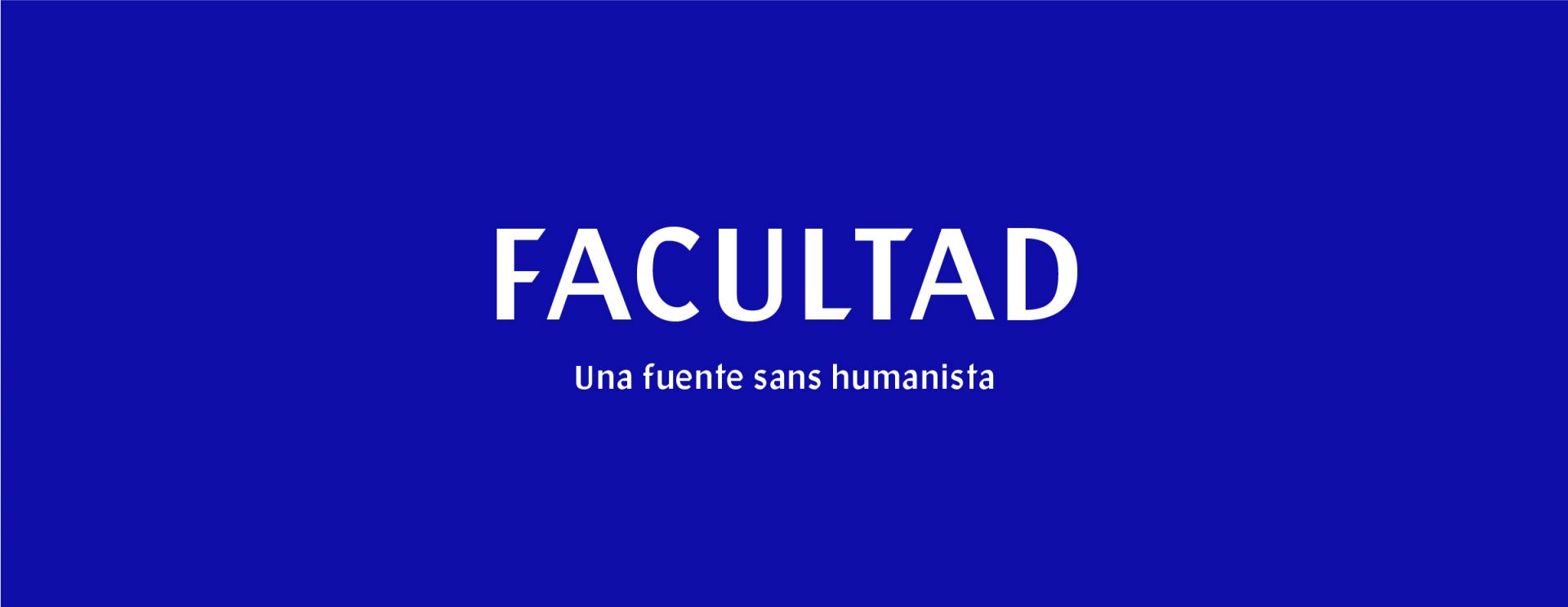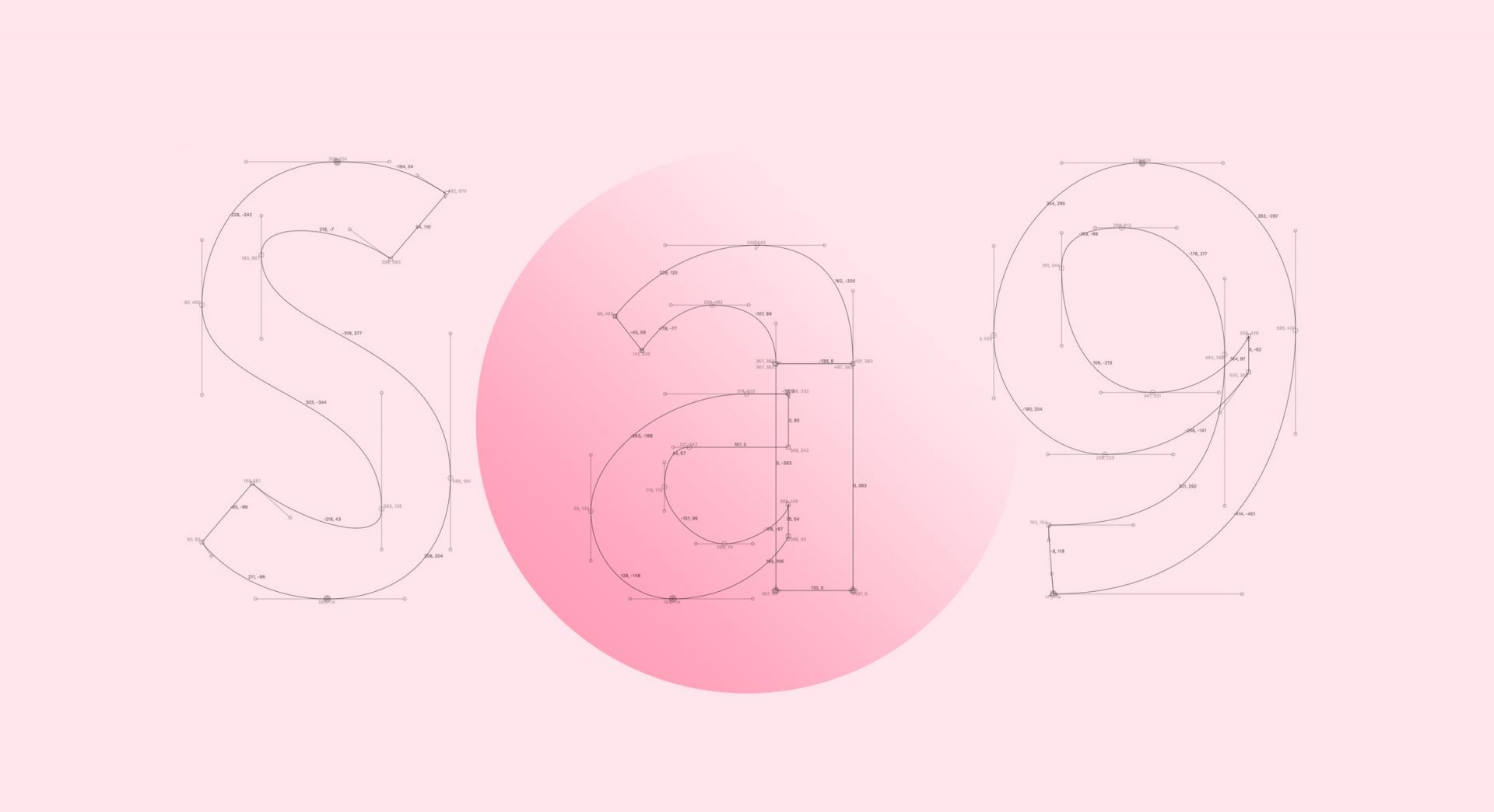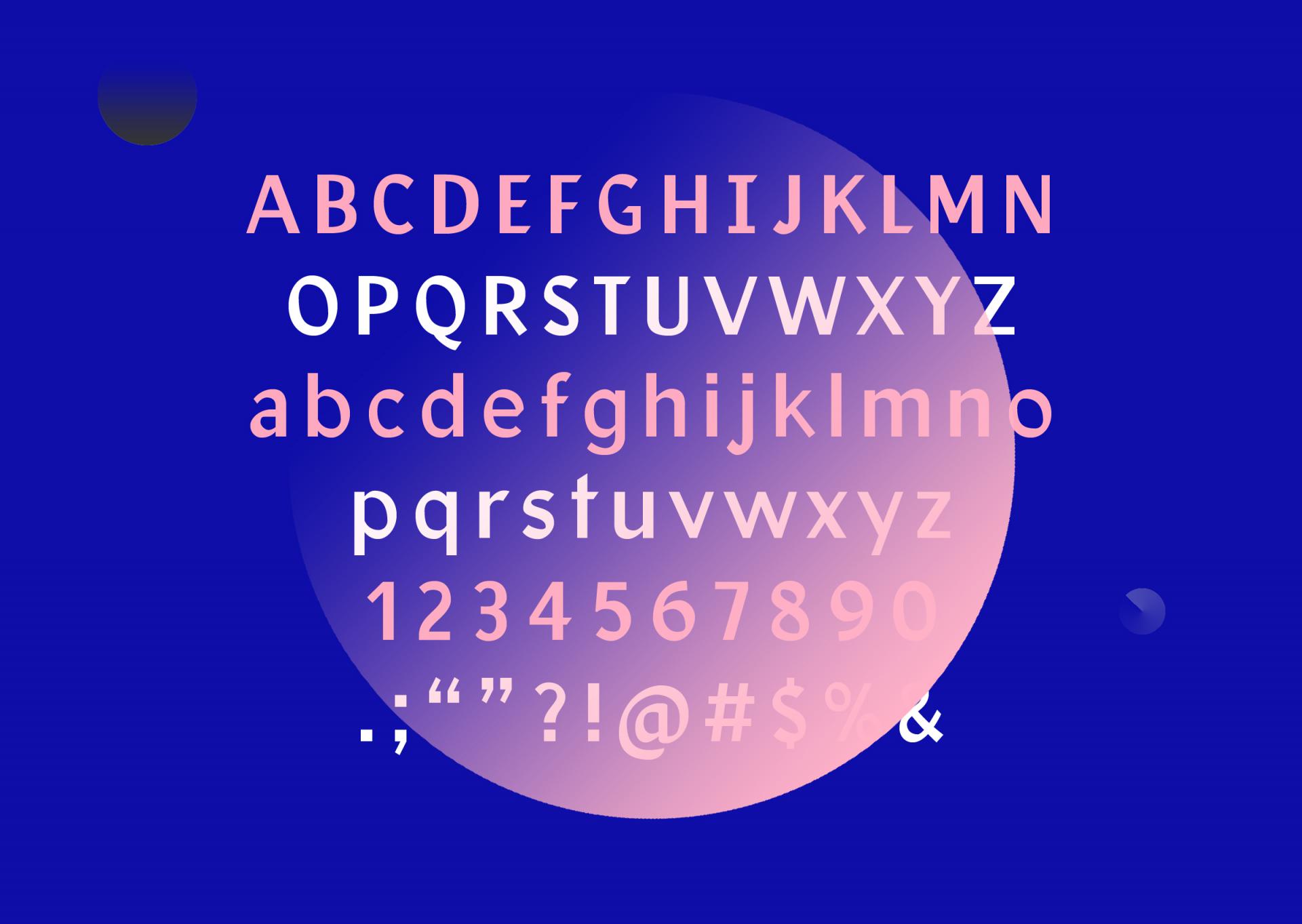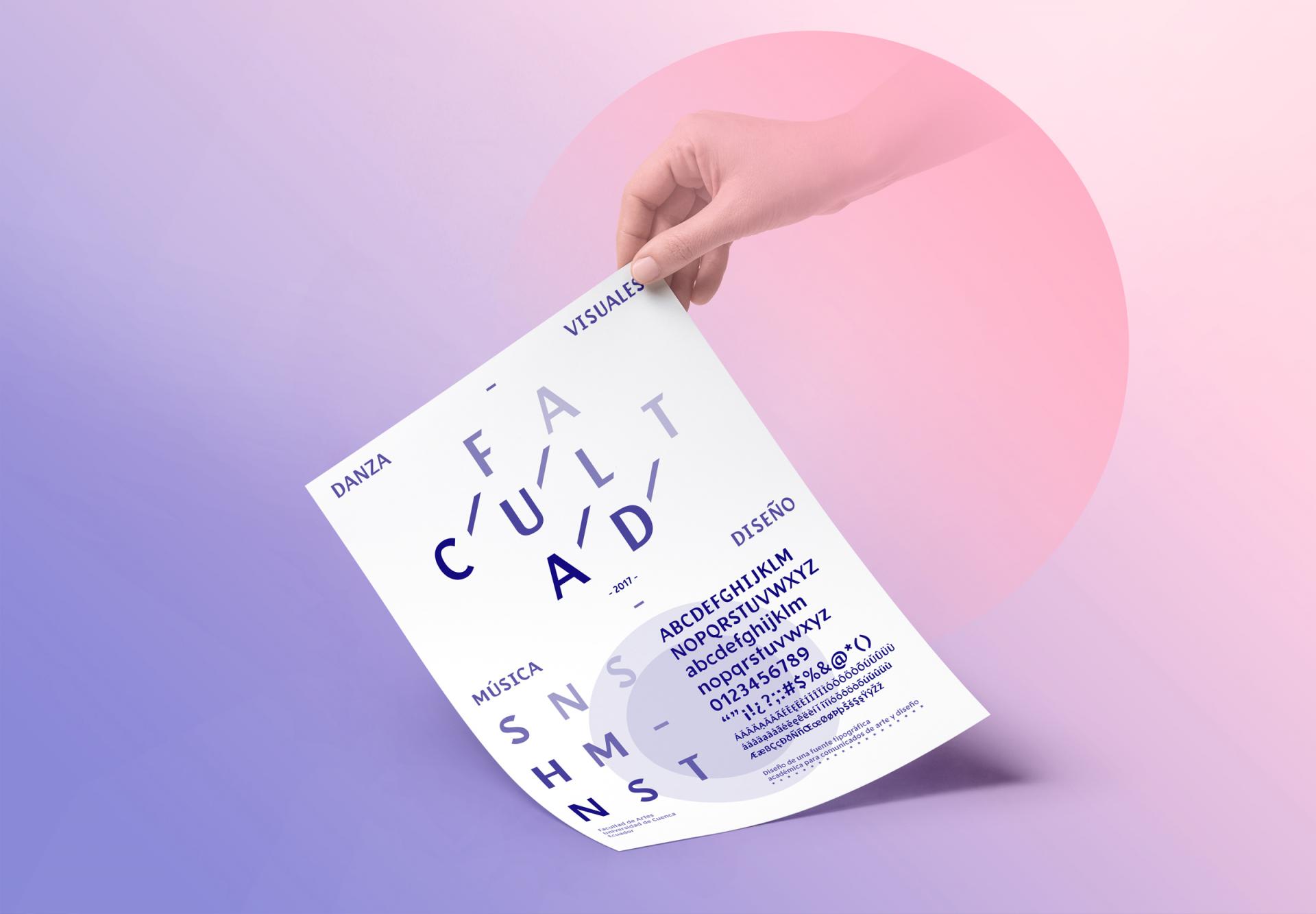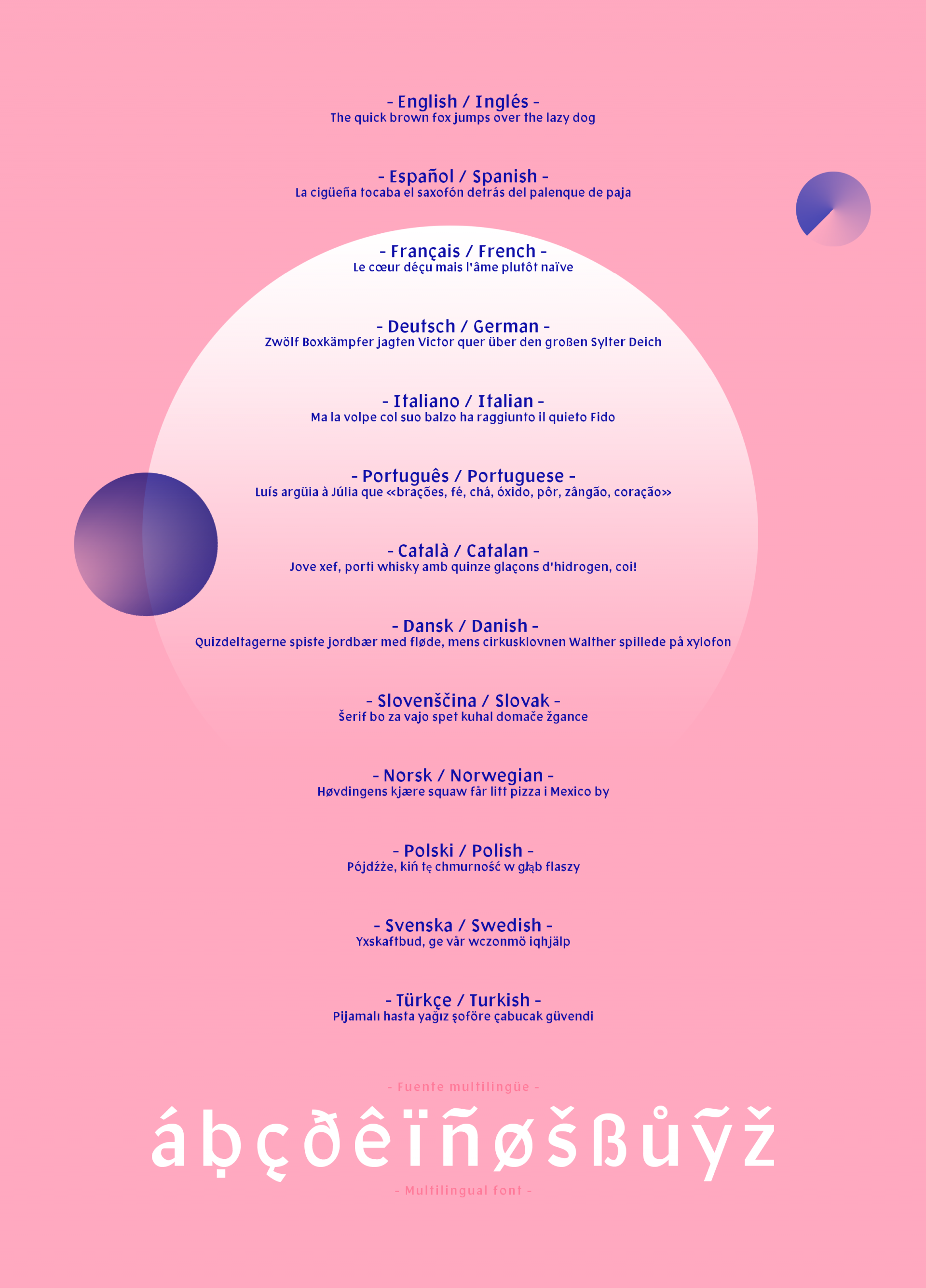
Typeface Facultad - Bộ chữ học thuật dành cho nhà thiết kế
Andrés Torres đã thiết kế bộ typeface học thuật dành cho giao tiếp nghệ thuật và thiết kế.
Sans Serif / Đa ngôn ngữ / 435 Glyph / OpenType Format.
Phát triển bởi Andrés Torres.
Dự án này tập trung sử dụng phương pháp kỹ thuật số và analog, khám phá hình thái của các ký hiệu hiện đại, nền tảng của các đường nét cổ điển để tạo nên bộ chữ có thể sử dụng cho các tiêu đề của Khoa Nghệ thuật, trường Đại học Cuenca, Ecuador.
Phương thức trên dựa vào cách tiếp cận mới mẻ khởi xướng bởi Karen Cheng trong quyển sách “Designing type”.